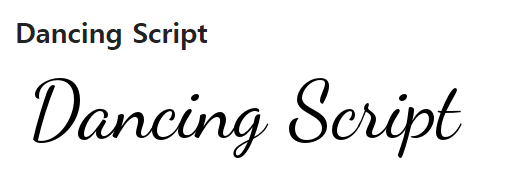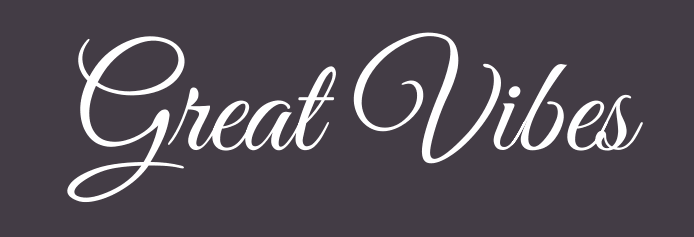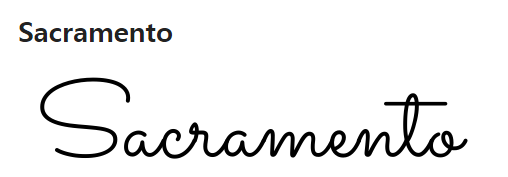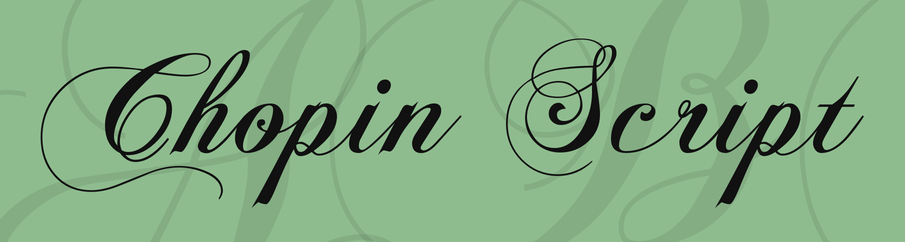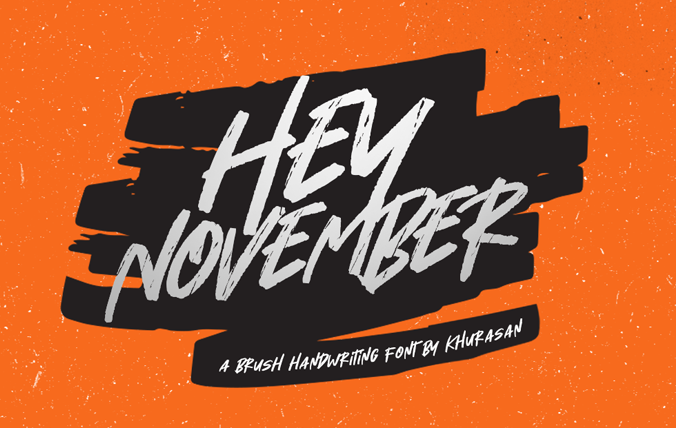
디자인 감각 살아있고 저작권 걱정까지 없는 상업용 무료 영문 필기체 폰트 찾기가 생각보다 쉽지 않은데요. 열심히 서치 해서 마음에 드는 폰트들을 찾아도 대부분 개인용만 무료이고, 상업용은 유료인 폰트들이 많습니다.
1, 댄싱 스크립트 폰트
가장 먼저 소개해 드릴 무료 영문 폰트는 댄싱 스크립트 폰트입니다. 폰트 굵기도 4가지로 다양하게 활용할 수 있어서 좋은데요. 활동적이면서 우아하고 멋스러운 영문 폰트가 필요할 때 사용하면 좋은 폰트입니다.
2, 그레이트 바이브 폰트
그레이트 바이브 폰트는 켈리그라피 느낌의 필기체 영문 폰트로 저작권 걱정 없이 로고나 타이틀에 사용하기 좋은 예쁜 영문 무료 폰트입니다. 그레이트 바이브 폰트를 사용하실 분들은 아래 폰트 이미지를 클릭하시면 바로 다운로드 받으실 수 있습니다.
3, 파리지앵 폰트
정갈하고 예쁜, 영문 무료 폰트인 파리지앵 폰트는 구글 폰트에서 찾은 폰트입니다.
4, 쁘띠 포멀 스크립트 폰트
고급스럽고 세련된 느낌의 쁘띠 포멀 스크립트 폰트는, 인쇄 출판에서도 많이 사용되는 서체입니다. 구글 폰트에서 다운로드 받을 수 있으면, 다운로드가 필요하신 분들은 아래 서체 이미지를 클릭하시면 바로 다운로드하실 수 있습니다.
5, 피뇽 스크립트 폰트
로맨틱한 라운드 핸드 스크립트 스타일의 피뇽 스크립트 폰트는 구글 폰트에서 다운로드 받을 수 있습니다.
세련되고 귀족적인 스타일로, 웨딩, 초대장, 밸런타인 등에 많이 사용되는 폰트이기도 합니다. 개인 및 상업용으로도 무료 사용이 가능한 폰트로, 서체가 필요하신 분들은 서체 이미지를 클릭해 주세요.
6, 플레이볼 폰트
플레이볼 폰트는, 이름에서 느껴지는 것처럼 운동 경기를 연상시키는 무료 영문 폰트입니다.
특히, 야구 배너에 사용하면 아주 좋을 것 같은 폰트인데요. 이밖에도 로고, 브랜딩, 명함, 초대장 등에 다양하게 사용하기 좋은 폰트입니다. 서체가 필요하신 분들은 서체 이미지를 클릭해 주세요.
7, 루즈 스크립트 폰트
구글 폰트에서 다운로드할 수 있는 루즈 스크립트 폰트는, 캐주얼하면서 부드러운 곡선 느낌의 무료 영문 폰트입니다. 루즈 스크립트 서체가 필요하신 분들은 서체 이미지를 클릭하시면 다운로드하실 수 있습니다.
8, 새크라멘토 폰트
새크라멘토 폰트는, 무료 상업용 영문 폰트로 핸드레터링 브로셔에서 영감을 받아 만든 서체입니다. 빈티지한 느낌의 헤드라인이나 타이들 등에 저작권 걱정 없이 사용하기 좋은 폰트입니다. 서체 이미지를 클릭하시며 다운로드하실 수 있습니다.
9, 쇼팽 스크립트 폰트
이름에서 알 수 있듯이, 쇼팽에서 영감을 받아 만든 쇼팽 스크립트 폰트는 로맨틱한 핸드라이팅 스타일의 폰트로 저작권 걱정 없이 무료로 사용할 수 있는 폰트입니다. 서체 이미지를 클릭하시면 다운로드하실 수 있습니다.
10, Hey November 폰트
Hey November 폰트는 헤드라인 등에 멋스럽게 사용하기 좋은 디자인 폰트로 제가 많이 사용하는 폰트 중 하나입니다. 디자인 퀄리티를 높여주는 폰트로, 상업용까지 무료로 사용할 수 있는 폰트입니다.